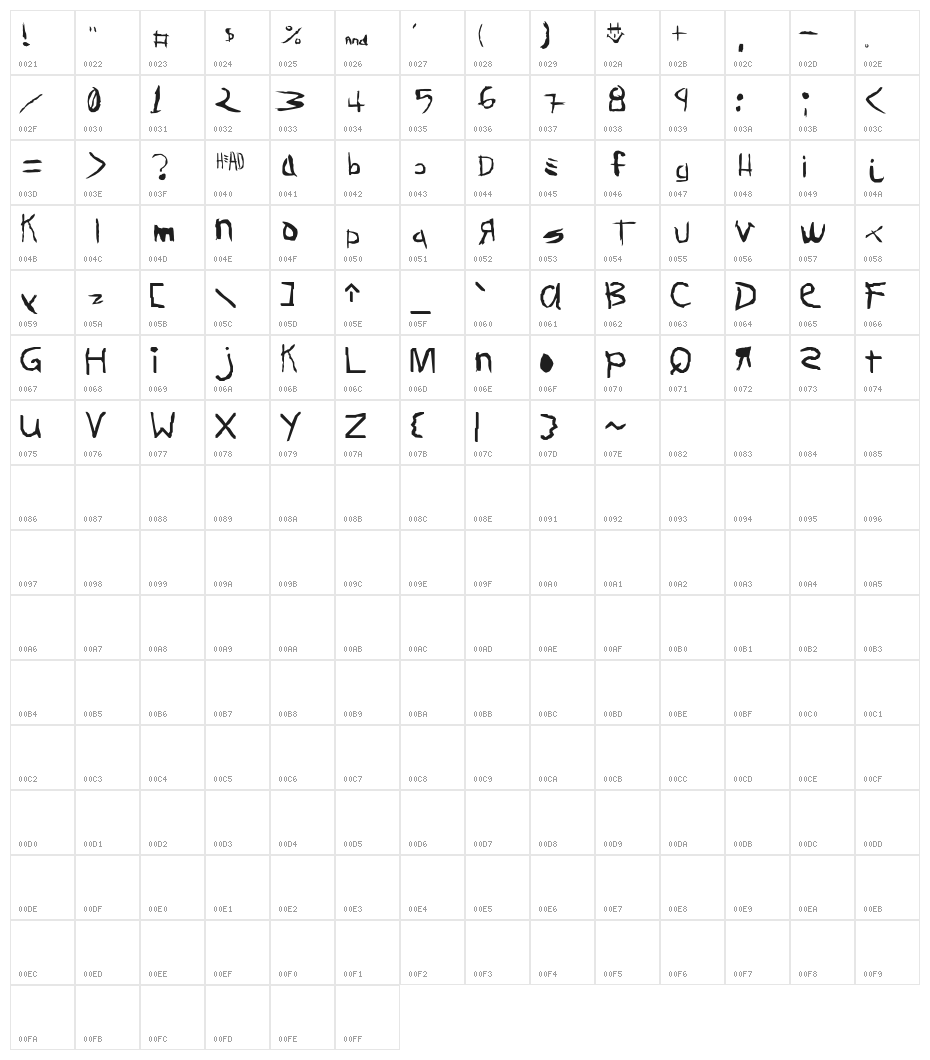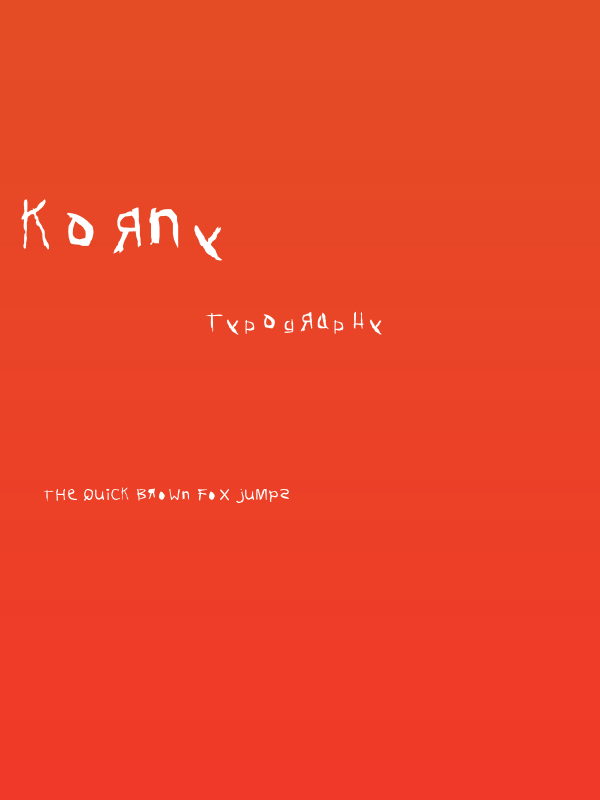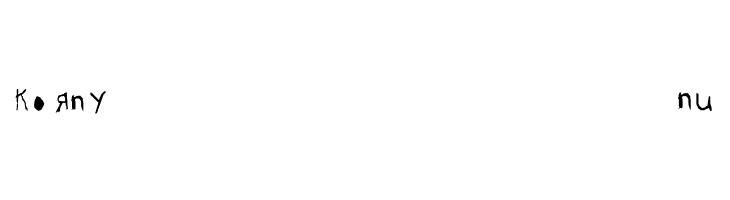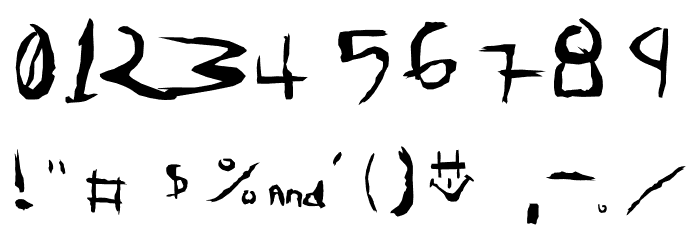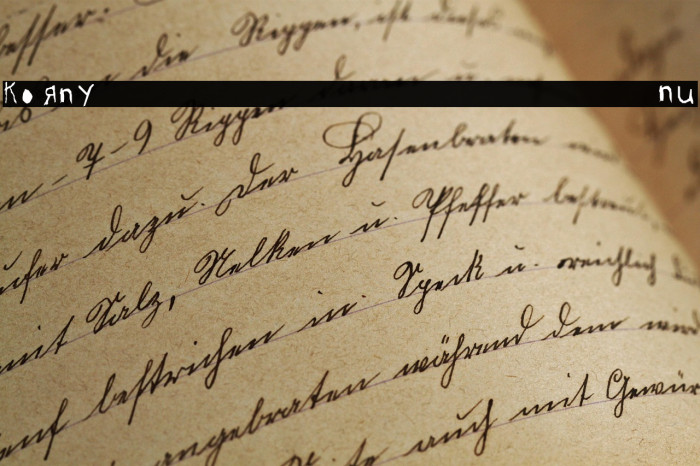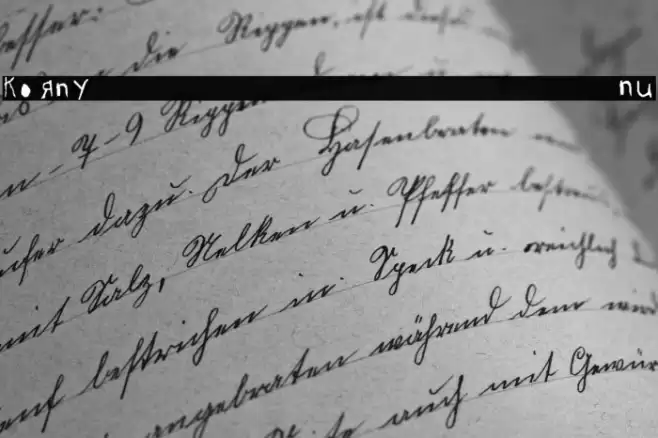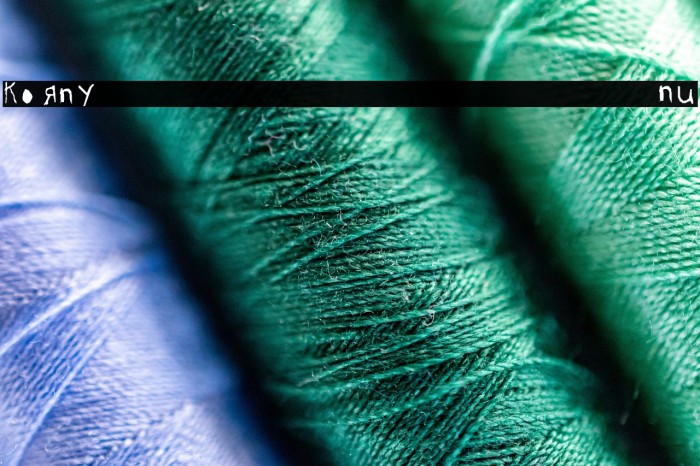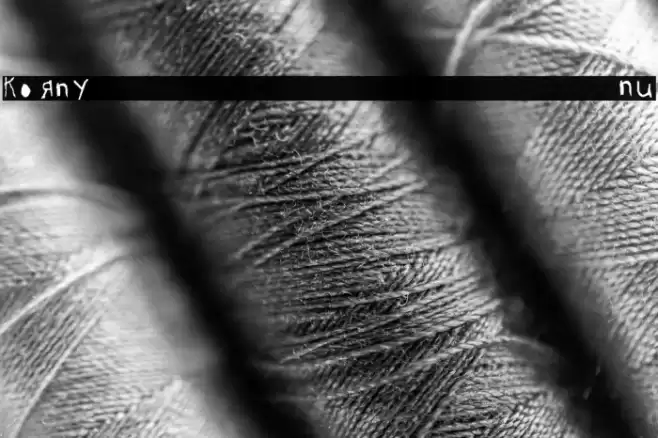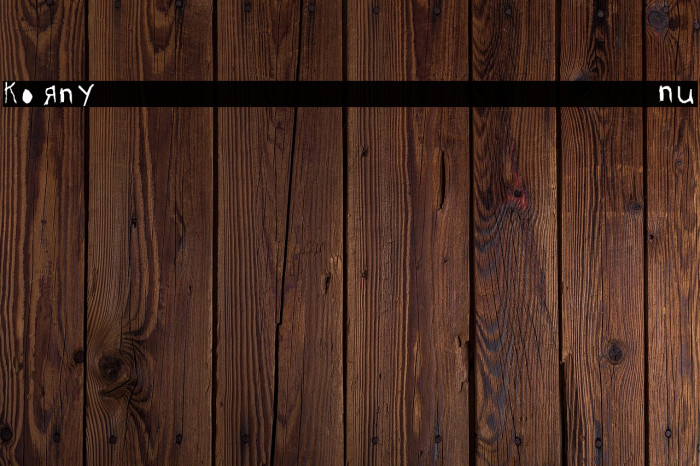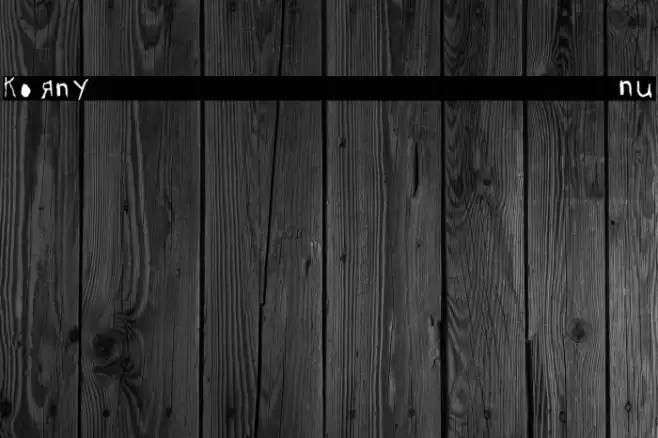
KoRny Nu Font
| Nome | KoRny Nu |
| Famiglia di caratteri | KoRny |
| Caso d'uso | Headlines, Logos, Creative projects |
| Progetti proposti | Ideal for children's books, creative posters, playful branding, and artistic invitations. |